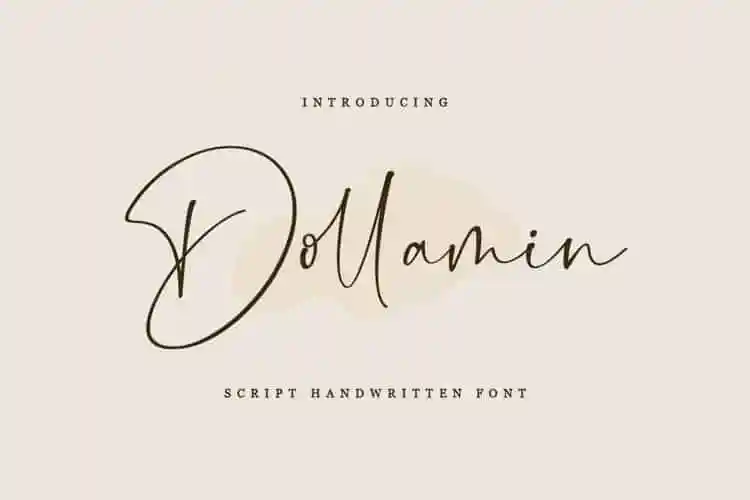
Dollamin Calligraphy Font – Download Grátis
A Dollamin Calligraphy Font é uma beleza tipográfica perfeita para criar uma série extensa de projetos gráficos. Embora seja um tipo de caligrafia escrita a mão, ela traz elegância para cada curva, criando um ar sofisticado e autêntico em cada letra. Esta fonte foi criada pelo Dav Studio e é perfeita para qualquer trabalho criativo onde você precisa de uma aparência delicada e personalizada. Seja para criar etiquetas de embalagem, design de marca, cartas de convite, decoração de papelaria, estilização de casamentos ou até mesmo gráficos de rede social e anúncios. Equipado com letras básicas, números, pontuação e suporte a múltiplas línguas, essa fonte é uma ótima adição para seu acervo de ferramentas gráficas. Experimente incorporar essa fonte ao seu próximo trabalho e veja como ela pode dar um toque especial aos seus projetos.